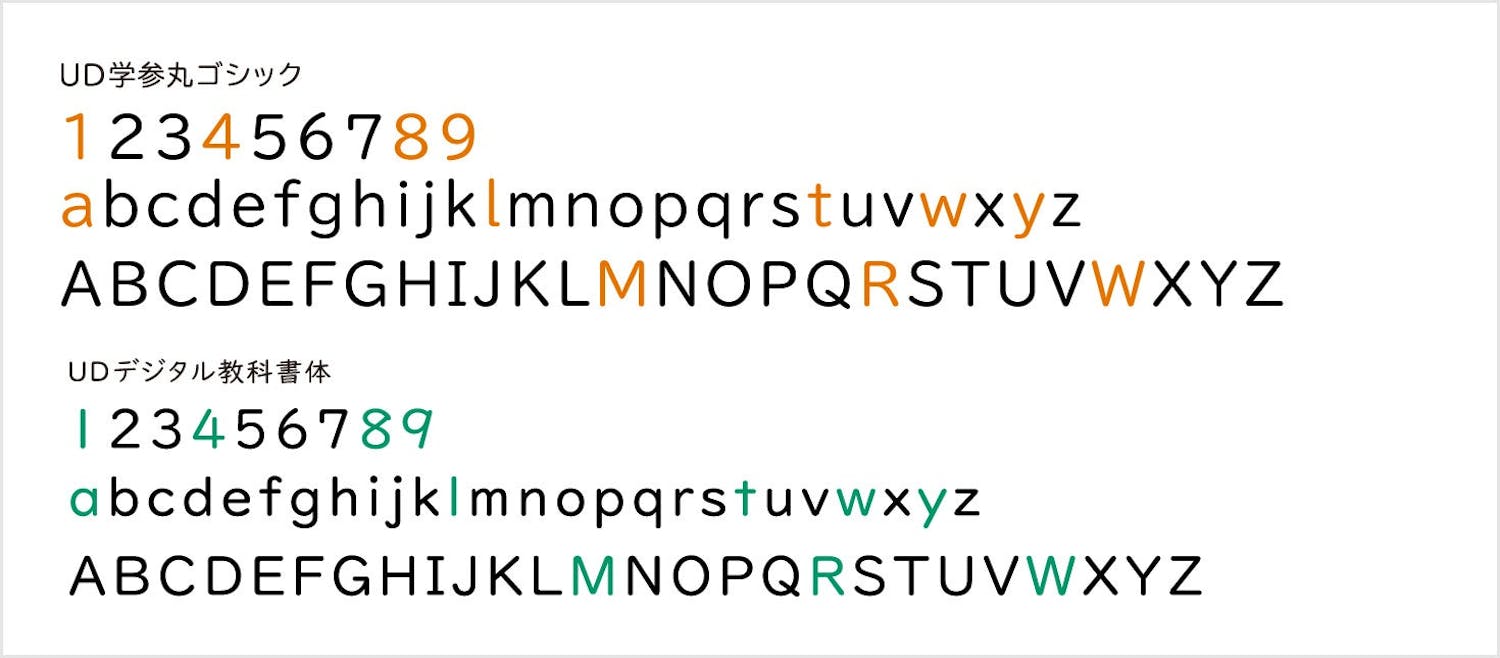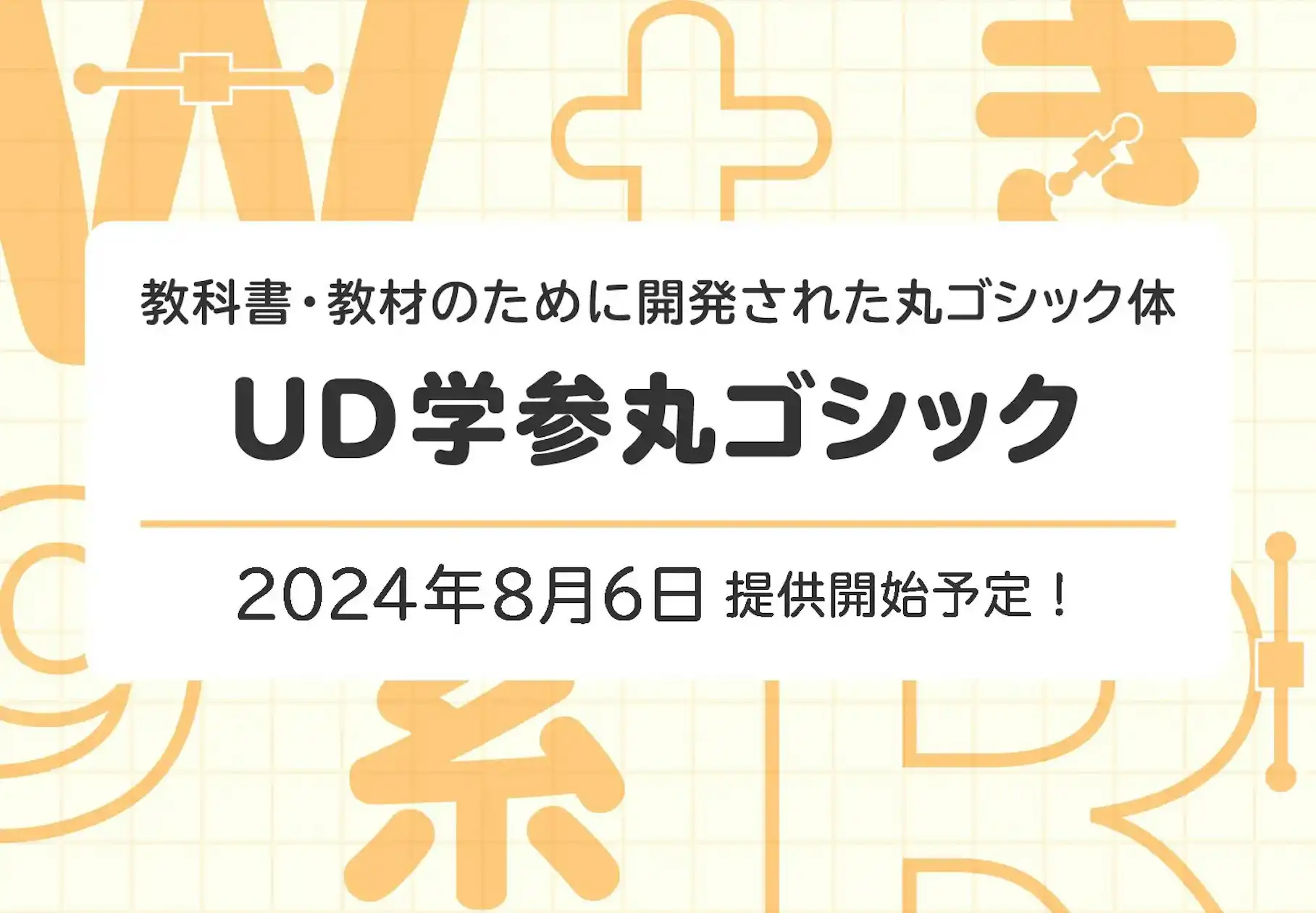
モリサワ、新書体「UD学参丸ゴシック」を提供開始!読みやすさに配慮した教科書向けフォント
「UD学参丸ゴシック」は、教科書や教材のために特別に開発された丸ゴシック体であり、文部科学省の学習指導要領の字形に準拠するよう設計されています。このため、読み書きに困難さを感じる児童・生徒を含む多くの子どもたちの学習を支援することが期待されます。
以下のポイントが特徴です:
• 文字の大きさ: ひと文字ひと文字が大きく見えるように工夫されており、お年寄りやロービジョンの方にも読みやすい設計になっています。ロービジョンの方を対象とした検証でも高い評価を受けています。
• 英数字の形状: ロービジョンの方へのヒアリングを踏まえ、読み間違えにくい形状を採用。「1」と「l(小文字エル)」や「a」と「o」、「W」と「VV」などの混同を防ぐ工夫が施されています。
• 複数の書体との併用: 子どもたちの発達段階や使用目的に応じて、「BIZ UDゴシック」や「UDデジタル教科書体」など、他のUDフォントとの併用・使い分けが可能です。
福岡教育大学で行われたアンケート調査によると、約273名の学生の4割以上が「UD学参丸ゴシック」を最も英数字の形がはっきりわかる書体と評価した模様です。
• UD学参丸ゴシック R
• UD学参丸ゴシック B
• UD学参丸ゴシック H